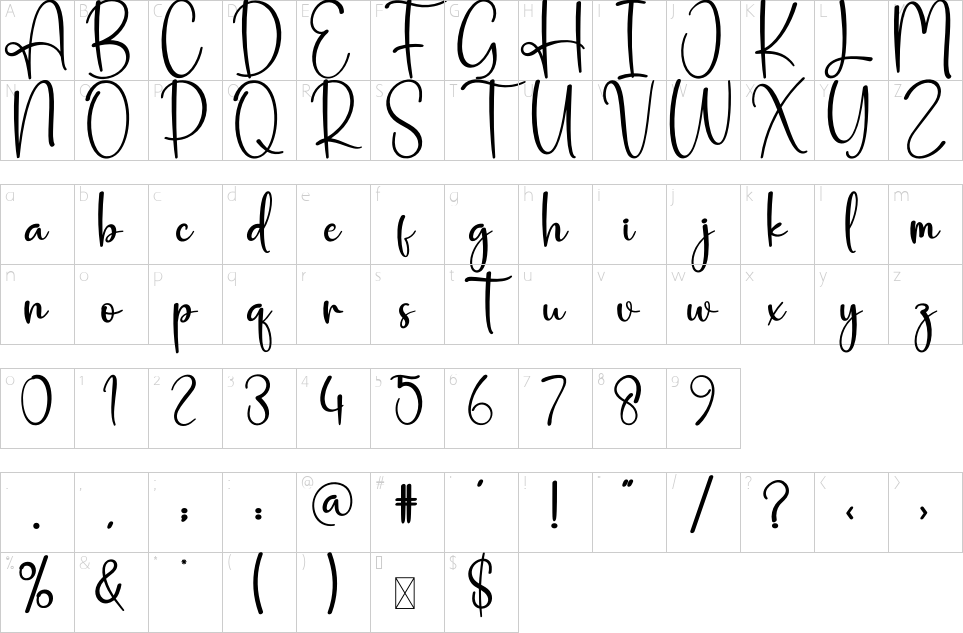
Descubra a magia da temporada de Natal com a Pink Santa font, um design leve e encantador criado por scratchones. Esta fonte digital é perfeita para aqueles que buscam uma aparição mais docemente colorida para as ocasiões festivas. Pink Santa é uma opção ideal para personalizar mensagens de Natal, decorações de natal e até mesmo para criar um toque alegre em documentos pessoais. Com uma cor rosa suave e um design elegante, esta fonte traz uma sensação de leveza e encanto que se adaptará perfeitamente aos momentos mais felizes do ano. Atualmente disponível para download gratuitamente, você pode experimentar a Pink Santa em sua próxima obra ou projeto. Com apenas um clique, transforme qualquer documento em um documento natalício encantador. Não deixe de explorar e descubra por si mesmo a magia desta fonte única.